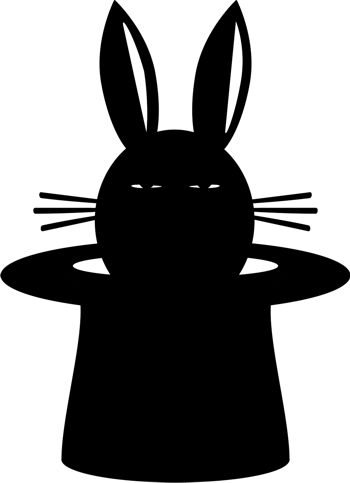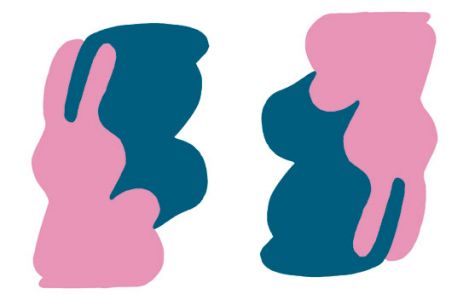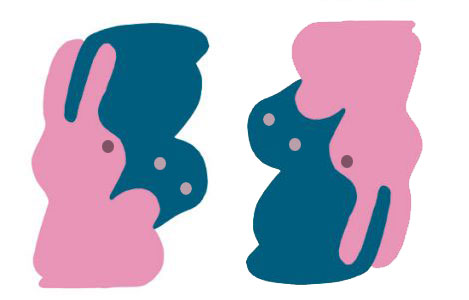
"einfach, erfrischend, anderer" Font für Zauberkün
Da bin ich ja jetzt ganz OFFENSICHTLICH in einer Zwickmühle ...
Wieviel Modifikation ist notwendig um aus der Adoption eine vertretbare Adaption zu machen?
Am Kopf und vor allem an den Augen möchte ich eigentlich nichts mehr verändern, von Veränderungen am Körper würde ich mich noch überzeugen lassen ...
Es geht ja nicht um eine rechtliche Frage (das Bild ist natürlich inzwischen frei), sondern darum, ob Du mit dieser Toulouse-Lautrec-1900-französisches-Varité-Assotiation, die mit der Katze geweckt wird, gut bedient bist. Das wäre ja nicht erfrischend andere, sondern eben konvetionelle Zauberei (was im übrigen auch dem entspricht, was ich aus den Bilder auf Deiner Seite herrauslese). Das muss ja nicht schlecht sein, warum sollte klassische Zauberei nicht ihr Publikum finden? Das für mich gelungenste Gastspielangebot der letzten Monate lautete so:
Ja, ich mache auch so einen Tucholsky-/Brecht-/Weil-Liederabend. Aber ich singe besser als die anderen, habe schönere Beine und die Gags meiner Überleitungen sitzen.
Es geht ja nicht um eine rechtliche Frage [...]
Naja, meine moralische Seite fühlt sich mittlerweile auch angesprochen!
[...] sondern darum, ob Du mit dieser Toulouse-Lautrec-1900-französisches-Varité-Assotiation, die mit der Katze geweckt wird, gut bedient bist. Das wäre ja nicht erfrischend andere, sondern eben konvetionelle Zauberei (was im übrigen auch dem entspricht, was ich aus den Bilder auf Deiner Seite herrauslese). Das muss ja nicht schlecht sein, warum sollte klassische Zauberei nicht ihr Publikum finden?
Es ist erstaunlich wie sich die Ausagen von Fachleuten unabhängig voneinander decken. Ein Werbetexter der mal einen Blick auf meinen Flyer geworfen hat, hat auch eben diese Diskrepanz (in meinen Texten) moniert.
Diskrepanz als Stilmittel einzusetzen wäre mein Wunsch - daß mir das noch nicht annähernd gelungen ist, ist mir durchaus bewußt.
Ähnlich wie mein Künstlername hat auch diese Katze IHRE Geschichte, und ich denke, dass das eine gute Grundlage für Identität ist.
und einen kleines gimmick – ich habe neulich visitenkarten gesehen
die waren wie eine art pop-up-buch gestaltet, allerdings nicht zum aufpoppen sondern mit diesen schiebereglern.
stell dir mal vor auf deiner vk wäre ein weißes kanninchen welches man
mittels schieberegler aus einem hut zaubern könnte – sowas würde
den kunden den du ansprechen willst sicher ein lachen ins gesicht zaubern
und darauf hin würde er sich sicherlich deinen namen merken.
Sowas in der Art, RobertM? Lässt sich je nach Tempo ziehen/blättern wie ein Film/Daumenkino (bloß schnell geknipst – ist nicht von mir).
Noch mal zurück zu den Visitenkarten:
Solche gebogenen wie die "Kosten/Nutzen" Beispiele habe ich mal von einem Zauberkünstler bekommen, wir waren am selben Event engagiert. Daß ich die Dinger aufgehoben habe, spricht dafür, daß die optische Täuschung effektvoll war, denn eine wichtige Aufgabe hat die Karte erfüllt, nämlich, schon mal nicht sofort weggeschmissen zu werden. Aber sie paßt nicht in normale Visitenkartensammelordner, und das kann bei Geschäftskundschaft auch negativ wirken.
Jedenfalls könnte ich mir eine optische Täuschung als Teil der Visitenkartengestaltung bei einem Zauberkünstler gut vorstellen.
(Während schwarze Katzen bei mir persönlich assoziativ eher unangenehm besetzt sind).
dass hier jede Menge sprudelnde Geister im Forum sitzen, dürftest du ja mittlerweile bemerkt haben. :-) Bei all den schönen Ideen empfehle ich dir aber, vorerst über deine Haltung nachzudenken, wie du in Erinnerung bleiben willst. Deine Auftraggeber suchen wahrscheinlich jemanden, der schmückender Programmpunkt in einer Veranstaltung ist und die Leute begeistert. Da sollte dein grafischer Auftritt erkennen lassen, dass du es einfach drauf hast. Das sollte lässig sein und verschwenderisch mit Tricks umgehen, also souverän daher kommen. Eine kleine Augenspielerei sei da erlaubt:
(Serviervorschlag)
Wenn du an der Katze hängst, lass sie da, aber mach eine eigene, sonst hast du immer die Atmosphäre von rotem Plüsch und Tüllröcken um dich rum. Für mich hat die Toulouse-Katze immer etwas alten Kinositzen.
Wenn du dauerhaft und kontinuierlich wahrgenommen werden willst, lass dir ein Erscheinungsbild machen, dass deine Belange regelt. Wenn du professionell wahrgenommen werden willst, musst du professionell auftreten und die visuellen Erwartungen bedienen.
Christians Idee mit den verschwindenden Buchstaben finde ich extrem passend und gelungen. Applaus.
Es geht wohl weniger ums Rechtliche als um allzu Offensichtliche, oder? ...
Da bin ich ja jetzt ganz OFFENSICHTLICH in einer Zwickmühle ...
Wieviel Modifikation ist notwendig um aus der Adoption eine vertretbare Adaption zu machen?
Am Kopf und vor allem an den Augen möchte ich eigentlich nichts mehr verändern, von Veränderungen am Körper würde ich mich noch überzeugen lassen ...
Ja Bergbert, du darfst da Augen reinstanzen.
Zaubert.
Ich hatte gestern ein sehr langes und langweiliges Telefonat. Nebenbei hab ich mal einen minimalistischeren, aber dafür durchtriebeneren Hasen gemacht: